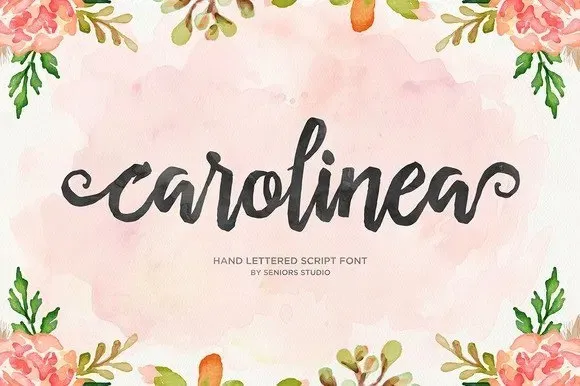
Carolinea Font – Download Grátis
A Carolinea é uma tipografia script elaborada a mão que combina traços de caneta e tinta para criar um estilo de calligrafia tradicional, com linhas onduladas desajeitadas e formas orgânicas. Este conjunto de 235+ caracteres inclui alternativas de inicial e final e ornamentos, tornando-a uma opção versátil para diversos ambientes design. Além disso, ela oferece suporte a múltiplas línguas, permitindo um uso global sem preocupações. Se você está procurando por uma tipografia que transmite personalidade e sofisticação ao mesmo tempo, a Carolinea pode ser perfeita para seu projeto. Hamilton é o designer responsável pela criação desta fonte, resultando em uma peça única que combina elegância com um toque de descontração. A qualidade da Carolinea não só torna-a uma ótima opção para design gráfico, como também é ideal para branding personalizado e qualquer tipo de projeto onde você deseja destacar seu estilo ou mensagem de forma atraente e única.